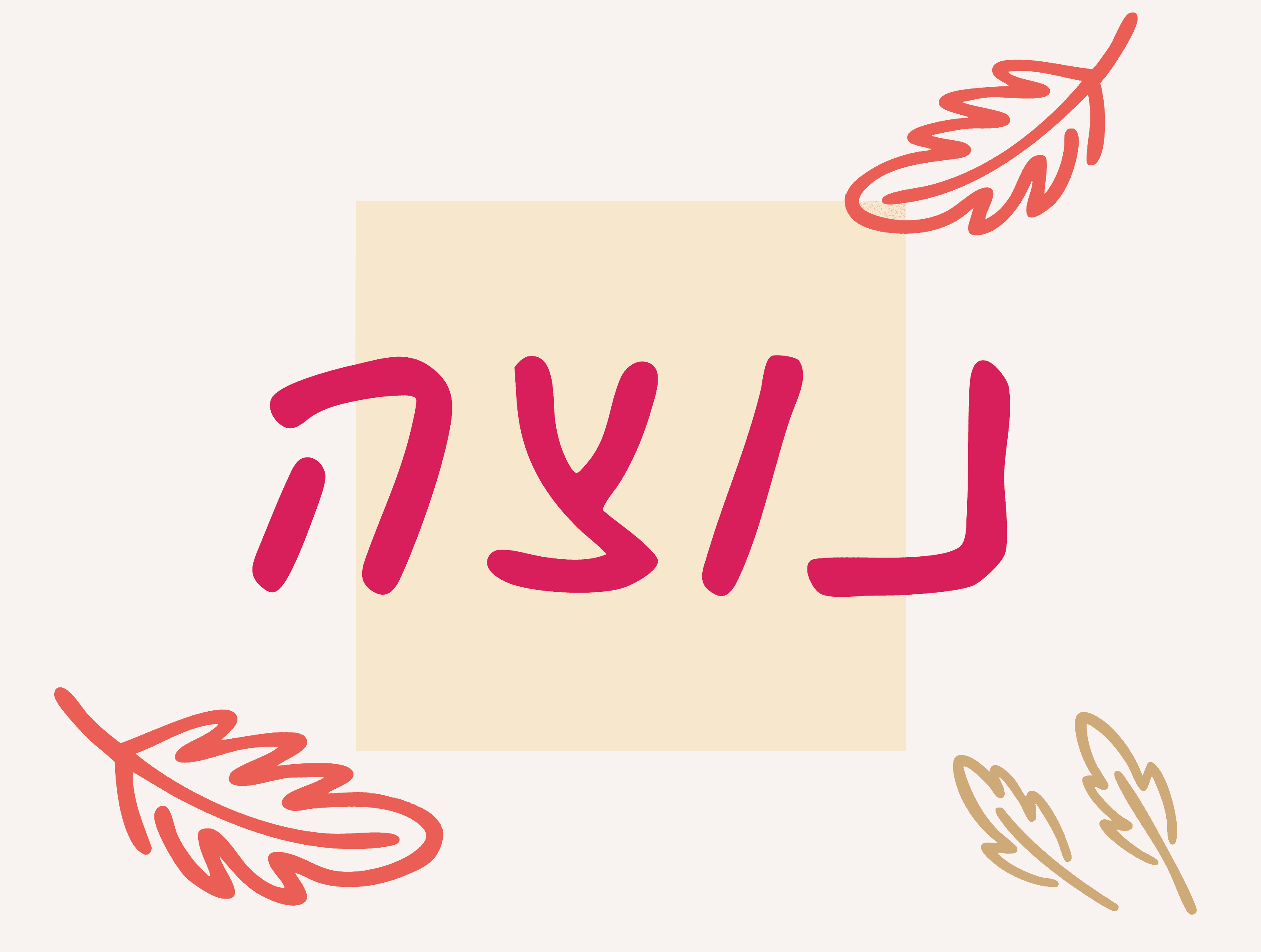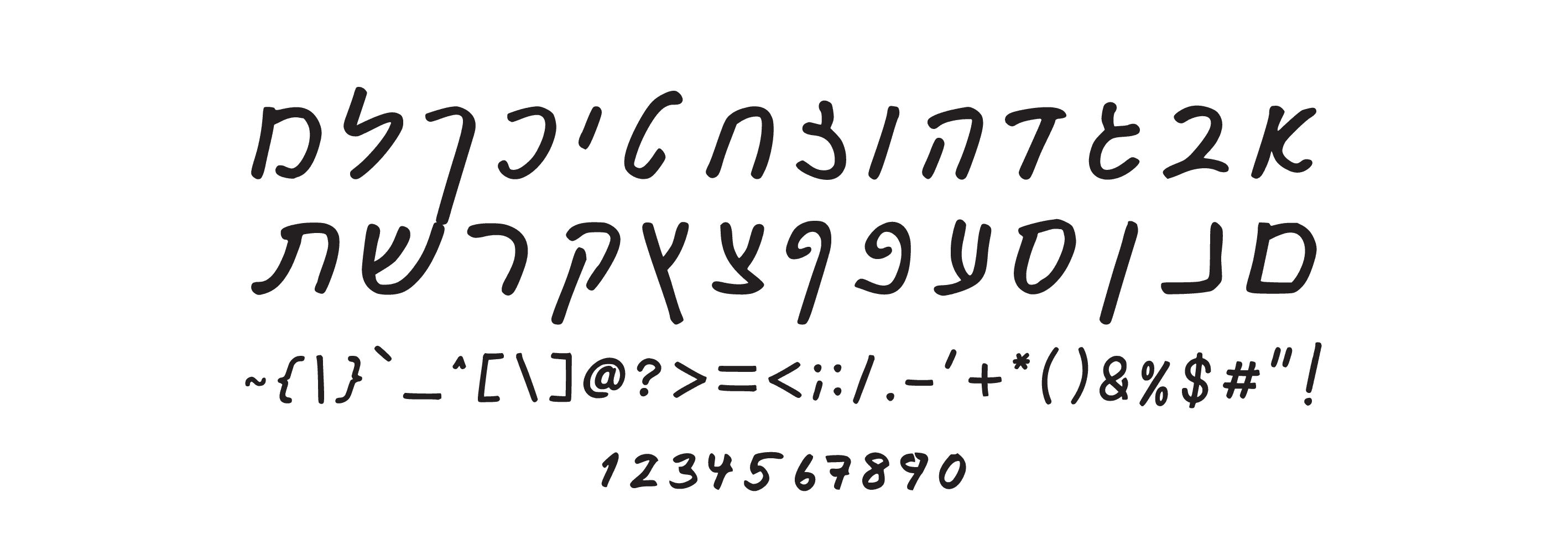
פונט נוצה
פונט עברי בכתב יד רך, קליל ואישי, מושלם לעיצובים טבעיים, נשיים ורומנטיים.
נוצה — הפונט של הלבבות הקטנים
יש פונטים שמזכירים לך לחייך.
נוצה הוא פונט כתב-יד עברי רך, קליל וחמים, עם קווים חופשיים ועדינים שמרגישים כאילו צוירו ביד אוהבת.
הוא משלב בין פשטות נעימה לאסתטיקה עגולה ומזמינה, ויוצר תחושת רוך, שלווה וטבעיות בכל מילה.
מושלם למי שמחפש עיצוב נשי, טבעי, אישי ומלא חמימות.
איפה הוא מרגיש בבית?
🪶 עיצובים עם ניחוח טבעי ועדין
🪶 הזמנות לחתונות, ימי הולדת ואירועים משפחתיים
🪶 לוגואים למותגים נשיים או מוצרים בעבודת יד
🪶 פוסטים ברשתות חברתיות שרוצים לחבק בעין
למי הוא מתאים?
למעצבים שרוצים להוסיף חמימות, רכות וטבעיות לכל עיצוב.